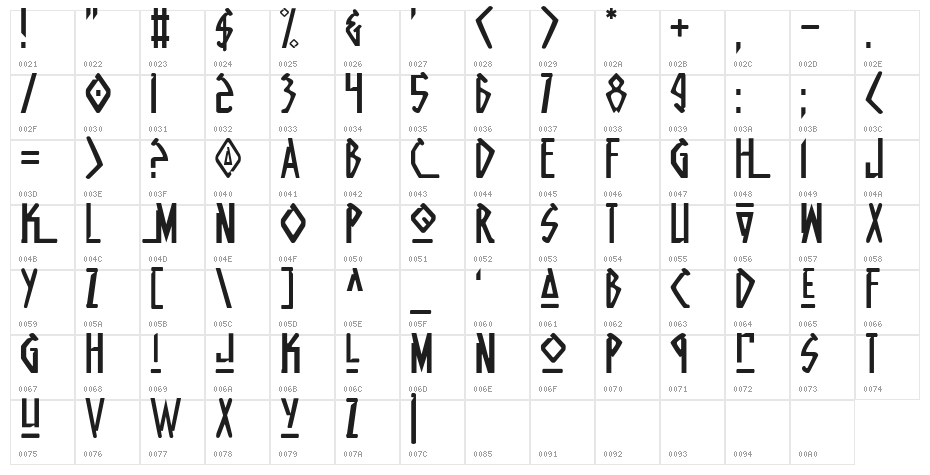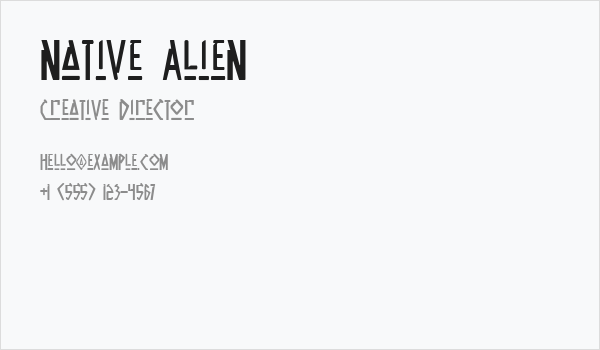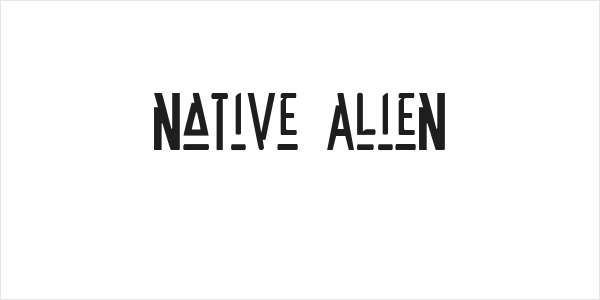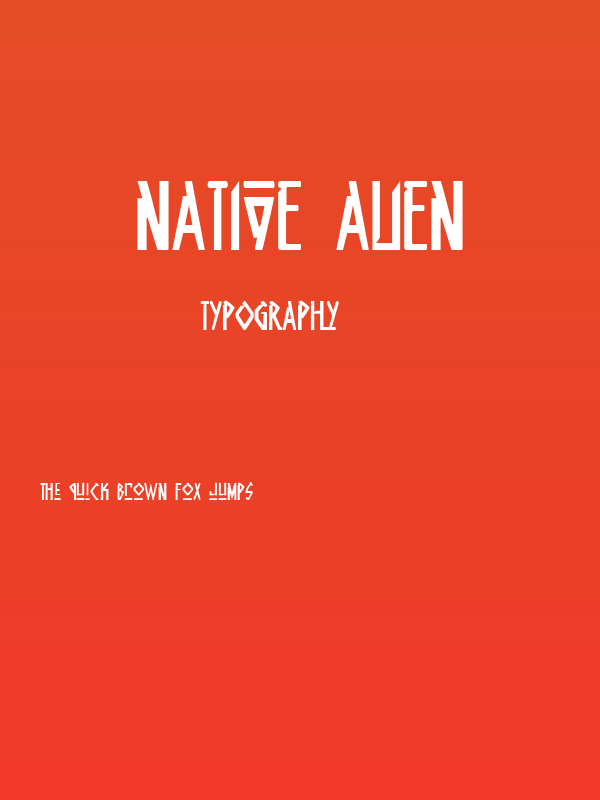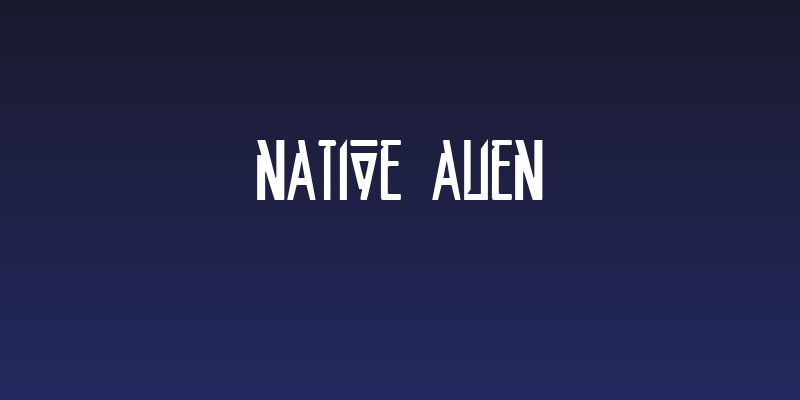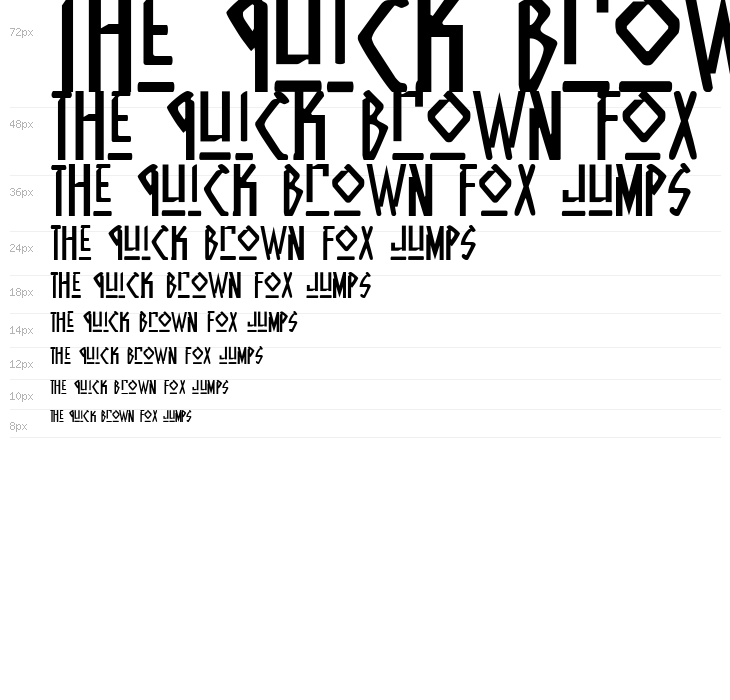
Native Alien Font
| कंट्रास्ट | High |
| समग्र शैली | Futuristic, Decorative |
| उपयोग का मामला | Headlines, Logos, Posters |
| सुझाए गए प्रोजेक्ट | Ideal for sci-fi themed posters, video game titles, and creative branding projects that require a unique, standout font. |